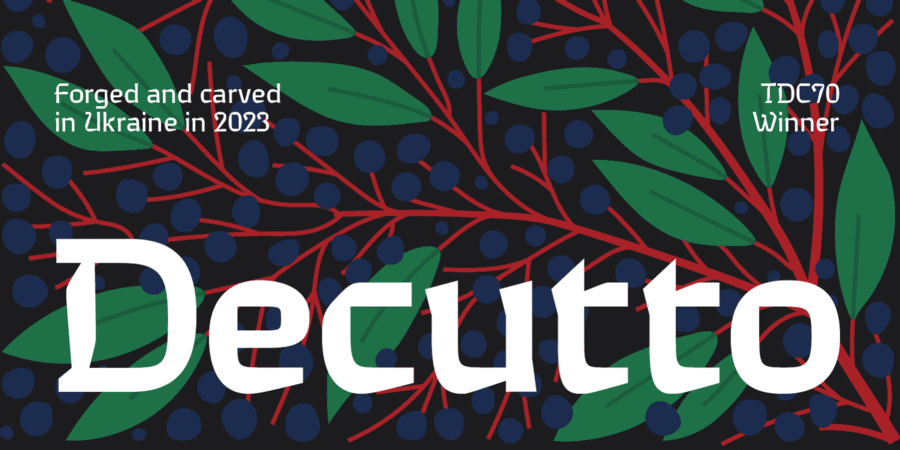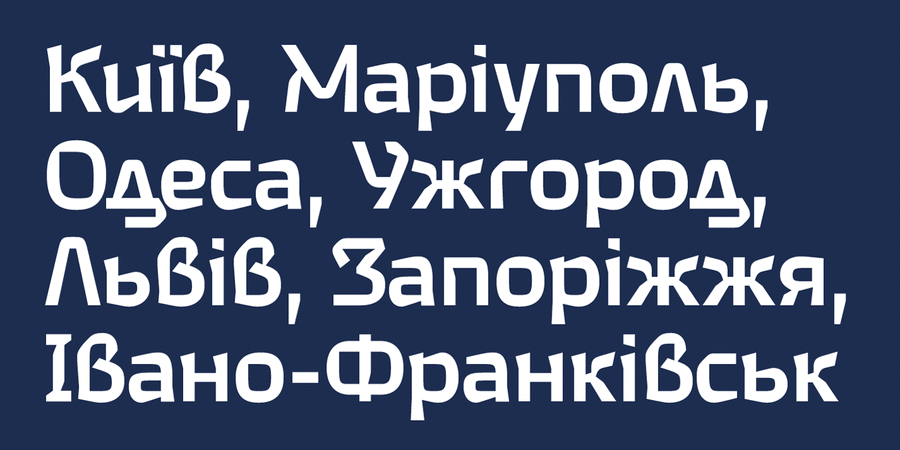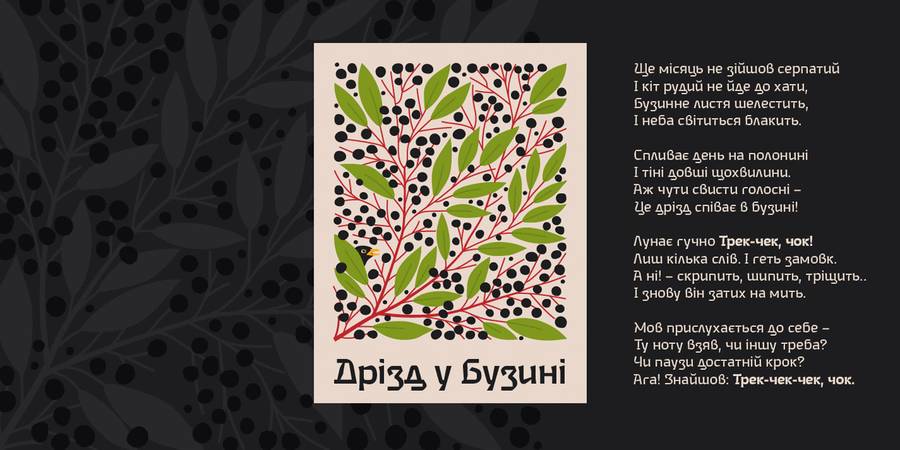
Decutto — це нео-гротеск, що бере маріонеткову формулу та деякі ідеї готичного письма та запаковує їх в малоконтрастний беззасічковий дизайн. Шрифт має відзнаку TDC Certificate of Typographic Excellence. Його назва грає виразами “off cut” і “cut to”, які виражають його ключову особливість — сучасна легкочитабельна форма літер декорована прямими різьбленими гранями, що надає шрифту чіткий і спрощений вигляд, як у старої карбованої монети.
Форма літер має яскраво виражені риси М-формули Вільяма Двіггінса, що робить загальну текстуру чіткішою та створює певний візуальний контраст між округлою зовнішньою чорною формою та прямокутною внутрішньою білою контрформою. Це спрощення робить текст чітким і різким у дрібному розмірі та дещо манерним у заголовку. Шрифт також отримав деякі риси готичного письма, такі як діагональні каліграфічні штрихи у великих літерах, ледь помітну трикутну засічку у верхньому лівому куті малих літер, та потовщення наприкінці верхніх і нижніх виносних елементів. Стилі: Light, Regular, Medium, Bold. Промо зображення використовують ілюстрацію з серії Танок Смерті Ганса Гольбейна Молодшого, а також елементи англійських середньовічних карбованих монет. Шрифт розробив Михайло Рафайлик у 2023 році і значно дороблений у 2024. Світ ловив мене, та не спіймав!